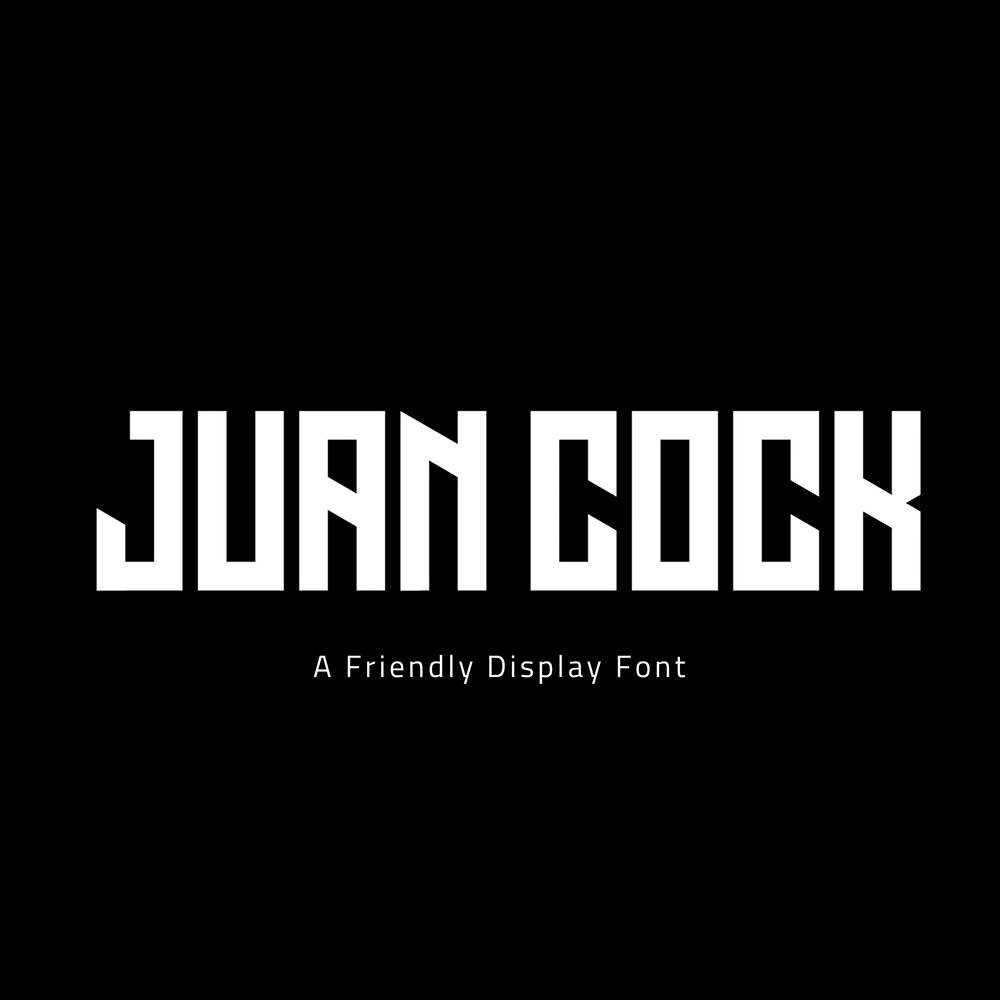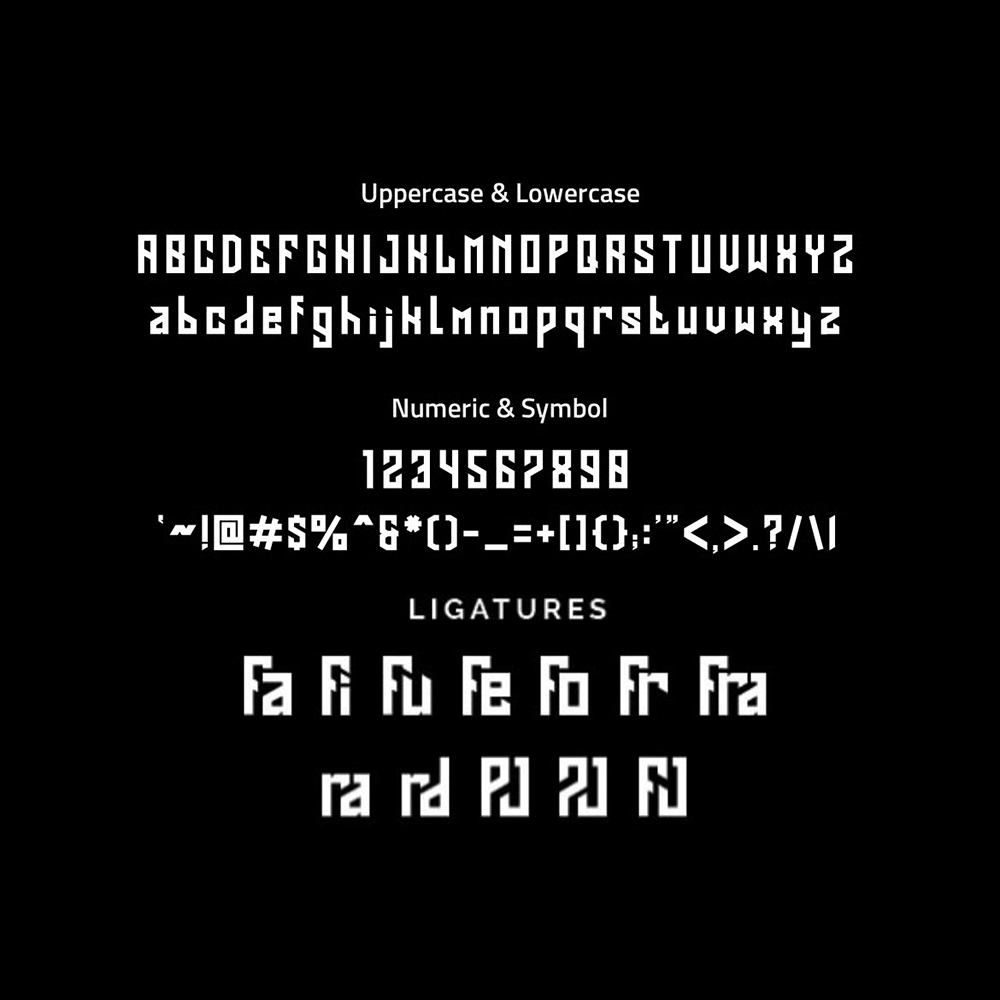
دانلود فونت انگلیسی Juan Cock Font
فونت پرمیوم و انگلیسی Juan Cock میتواند برای اهداف مختلفی مانند: لوگو، لوگوی ورزشگاه، لوگوی گروه، لوگوی قهرمان، لوگوی نظامی و اطلاعرسانی استفاده شود.
مزایای استفاده از فونت لاتین Juan Cock Font چیست؟